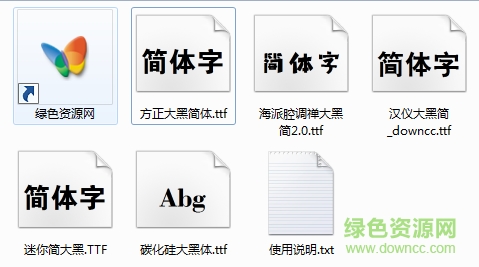
漢字的黑體是在現(xiàn)代印刷術(shù)傳入東方后依據(jù)西文無襯線體中的黑體所創(chuàng)造的。由于漢字筆劃多,小字黑體清晰度較差,所以一開始主要用于文章標(biāo)題。但隨著制字技術(shù)的精進(jìn),已有許多適用于正文的黑體字型。
黑體與白體相反,沒有襯線裝飾,筆劃粗壯有力,撇捺等筆畫不尖,使人易於閱讀。黑體是在現(xiàn)代印刷術(shù)傳入東方後依據(jù)西文無襯線體所創(chuàng)造的。所以黑體這個(gè)詞的范疇和無襯線字體是類似的。而宋體就可以被稱作襯線字體。